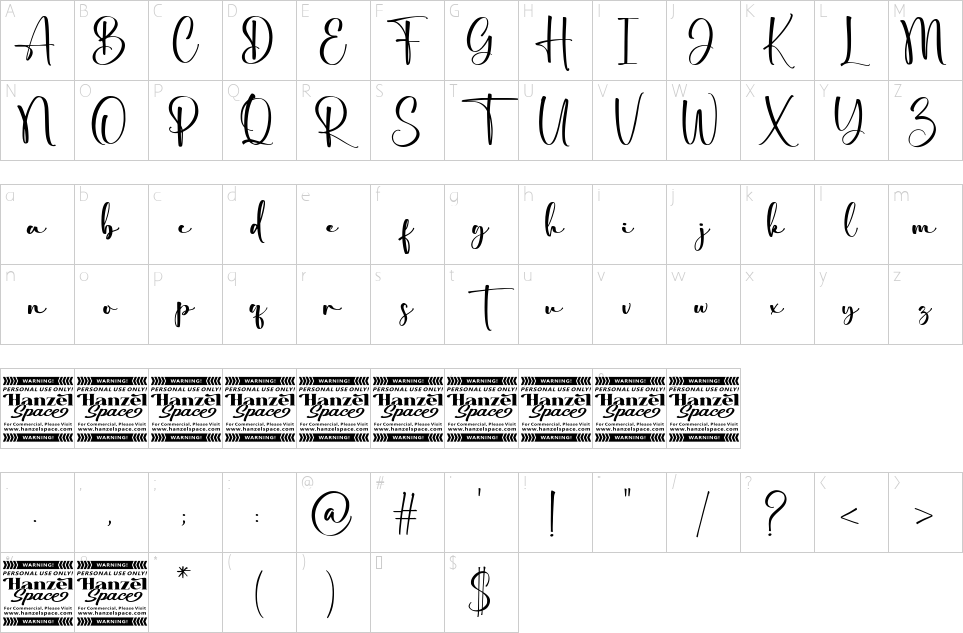
Airstone Font – Download Grátis
A airstone é uma fonte que transmite modernidade e elegância, perfeita para adicionar um toque sofisticado a seu design. Desenvolvida pela Hanzel Space, esta fonte tem sido baixada diversas vezes, demonstrando sua relevância e qualidade. Com um design minimalista e limpo, a airstone é um ótimo complemento para qualquer projeto gráfico, seja ele para fins comerciais ou pessoais. Se você está procurando por uma fonte que possa destacar seu design com elegância, a airstone é uma ótima escolha para seu portfólio. Recomendamos explorar sua versão gratuita para Windows e Mac para experimentar os benefícios de seu design único.